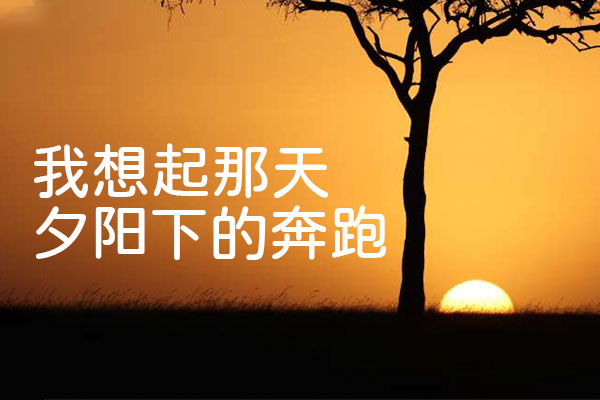
极影毁片圆
极影毁片圆是由中国大陆的九阳飞羽在 小衫圆体、思源黑体的基础上改造而成的字体。该字体以jf open粉圆为原型,使用江城圆体3.0、狮尾圆体SC作为增补,补全了Unicode中日韩统一表意文字,并且根据通用规范汉字表,修正了常用的简体汉字的笔画所整理而成的字体。值得一提的是,此款字体支持简体中文、繁体中文、日语,基本没有缺字,它的定位是整合和补缺。作者整理本字体的初衷是,很多媒体视频的字幕制作都在选择圆体作为主字幕正文。随着B站UP主、Youtuber等自媒体的兴起,能够有一个适合的视频字幕正文显示的字体能让大家更方便的“毁片”,这是一件很不错的事情。该字体仅有Medium(500W)这一种字重,主要用于字幕显示。该字体授权协议免费公开,个人及商用免费。
极影毁片圆效果预览